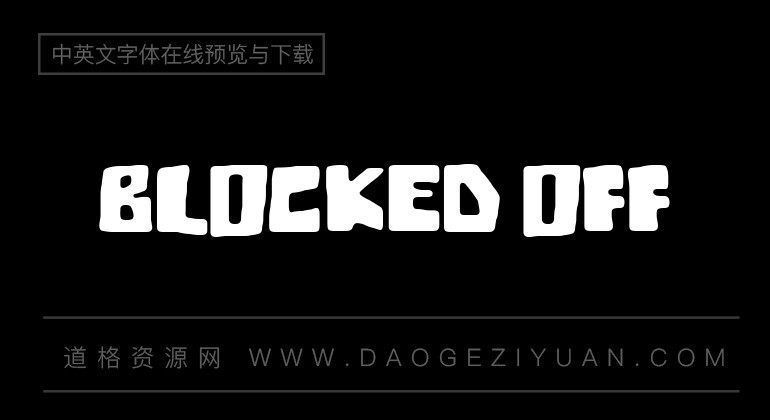
Blocked Off
Blocked Off 是一款现代护栏字体,由著名的设计师Kaiwa所设计,它的特点是拥有清晰的外观,简洁的线条,以及大胆的节奏。它的设计风格灵感来源于护栏,用于标识和醒目的消息,是一款非常适合在现代环境中使用的字体。它的字体支持所有常见的Unicode字符,可以用于多种语言,并且可以在屏幕上显示出精美的质感。
Blocked Off是一款非常不错的手写艺术字体,具有很好的视觉感,适合于文化类的宣传设计、商业类品牌的广告和产品包装设计以及个性化文字排版等较多场景。